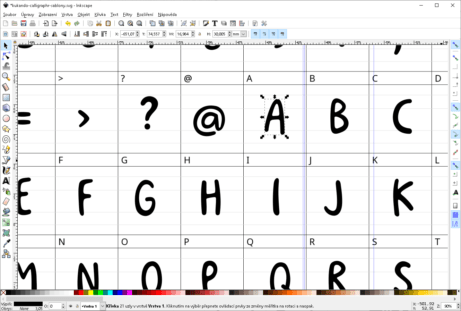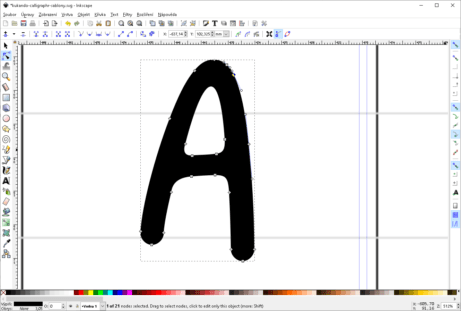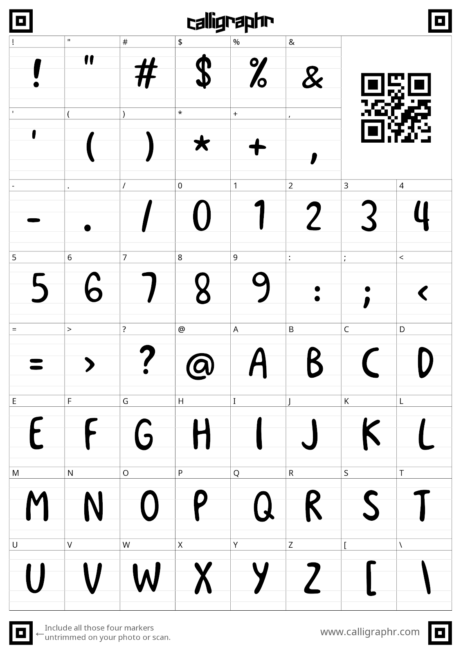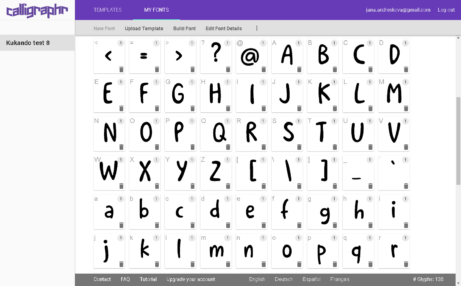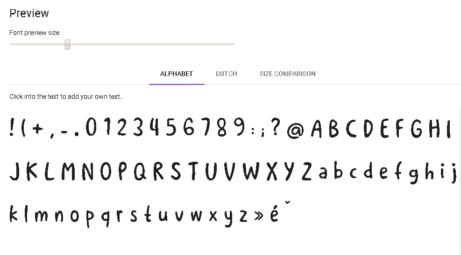
Jak moc je těžké navrhnout si vlastní font?
Otázka, která často následuje po období beznadějného hledání ručně psaného fontu, který by splňoval všechna kritéria náročného klienta, například:
- aby se dal přečíst
- aby měl českou diakritiku
- aby vypadal přesně tak, jak si ho představuje
Odpověď není lehká.
Na jednu stranu je jednoduché najít aplikaci „font maker“ (seznam máte na konci článku), která to umožňuje a bude se tvářit, že to je super easy a vlastní font může mít prakticky každý. Takže najdeme návod a jdeme na to, večer máme nové logo nebo vizitky. Na stranu druhou, já osobně zastávám názor, že fonty mají tvořit lidé, kteří to umí. Jinak vznikají „nepodarky“, které můžete s úspěchem použít třeba na pozvánky na narozeniny, nebo na plakátek BURZA U NÁS DOMA. Takové fonty pro osobní použití. V tomto kontextu se do toho určitě pusťte, naučíte se něco nového a je to zábava. I když rychlejší asi bude je napsat rukou.
Ale pokud výsledek chcete použít jako oficiální font a dát ho na produkty nebo stránky, tam bych byla velmi opatrná. Nemyslím si, že vytvořit font, který funguje jak esteticky, tak prakticky, je jednoduché. A už vůbec si nemyslím, že to zvládne každý, bez typografického vzdělání a zkušeností. Tedy až donedávna jsem si to myslela.
Ale pak jsem v přímém přenosu viděla, jak jeden takový vlastní font vznikl. A je skvělý. A tak vám chci tuto zkušenost zprostředkovat.
Asistovala jsem při anabázi hledání fontu, na jejímž konci bylo jasné, že jiná cesta, než “udělám si vlastní”, není. Proč? Autorka ho potřebovala použít na potisk produktů (trička, plechové hrníčky, atd.) zároveň se svými autorskými kresbami. Požadavky na font byly následující:
- font musel být použitelný v jakémkoli slově nebo větě. Nešlo o to napsat si v něm pár dopředu vyladěných slov, třeba logo, nebo motto. Musel fungovat jako plnohodnotný font, který si poradí s jakoukoli kombinací písmen.
- font musel respektovat charakter kresby obrázků, linky musely být vizuálně kompatibilní s tahy kresby na obrázcích. Jako kdyby používala na psaní i malbu stejný štětec.
Záměr nelehký, moc jsem tomu nevěřila, ale bingo, Jana Andrésková mě překvapila. Takže jsem změnila názor, připouštím, že za určitých okolností je možné vytvořit si slušný vlastní font a tady máte návod, jak na to.
V rozhovoru se dozvíte co je pro tvorbu vlastního písma nezbytné, jaký je ověřený nástroj a s jakými riziky musíte počítat.
1. Proč jsi šla cestou tvorby vlastního fontu?
Jsem výtvarnice a vždycky mě bavilo svoje obrázky doplňovat ručním písmem. Nikdy mě ale nenapadlo, že budu tvořit vlastní font. Změnilo se to až s Kukandem, což je značka mých obrázků pro děti. Na začátku byla dvojice slonů pro mé děti. Aby bylo jasné, čí je který slon, napadlo mě k nim přimalovat jména.
Pak se ukázalo, že děti mají ze svých jmen na obrázku obrovskou radost, takže jsem začala nabízet další obrázky zvířátek se jménem a zjistila jsem, že je o ně zájem. Když jsem začala přemýšlet o vlastním e-shopu a větší zakázkové výrobě, věděla jsem, že nemůžu každé jméno psát rukou, protože jmen, jejich variant, zdrobnělin a přezdívek je prostě moc. Myslela jsem si, že si na chvíli sednu k fontům zdarma a vyberu nějaký, který se bude k mým obrázkům hodit. Ale chyba lávky. Nehodil se ani jeden.
- Přešla jsem od českých fontů zdarma k českým fontům placeným… a nic.
- Přešla jsem od českých fontů k fontům bez diakritiky s tím, že si vytvoření diakritiky zaplatím navíc… a nic.
Žádný font svými tahy a energií neodpovídal obrázkům. Buď byl moc strohý, nebo moc dětský, nebo prostě divný. A tak přišla myšlenka na vlastní font. Věděla jsem, že na to nějaké nástroje existují, a začala jsem hledat návody.
2. Vyzkoušela jsi víc aplikací pro tvorbu fontu?
V prvním kroku jsem zkoušela profesionální nástroj na tvorbu fontů Glyphs, ale zjistila jsem, že má na mne příliš mnoho funkcí, a že by mi trvalo příliš dlouho se v něm zorientovat. Tak jsem přešla k aplikaci Calligraphr, která uměla přesně to, co jsem hledala. Můj hlavní požadavek byl, aby měla aplikace možnost jednoduše nahrát hotová písmena (včetně českých znaků), ze kterých pak vygeneruje font.
Nejdřív jsem Calligraphr otestovala ve verzi zdarma, která je ale omezená počtem znaků, takže na český font nestačí. Pro vytvoření fontu v češtině je potřeba placená verze. Není ale potřeba platit drahá licence, aplikace se platí formou měsíčního paušálu 8 dolarů. A za měsíc by se měl dát jeden font určitě stihnout 🙂
3. Popíšeš mi ve zkratce, jakým způsobem jsi při návrhu fontu postupovala?
Aplikace Calligraphr je koncipovaná tak, že si:
- vytisknete šablony
- do jednotlivých políček napíšete/nakreslíte znaky
- šablonu naskenujete a nahrajete do aplikace
- aplikace vygeneruje font.
Já jsem postupovala trošku jinak, protože jsem chtěla písmo tvořit v křivkách, nekreslit ho na papír. Daleko lépe se mi opravovaly nedokonalosti a ladily všechny detaily jednotlivých tahů.
Můj postup tedy byl:
- V programu Calligraphr jsem si nejdřív stáhla šablony, ve kterých jsou políčka pro jednotlivá písmena a znaky: